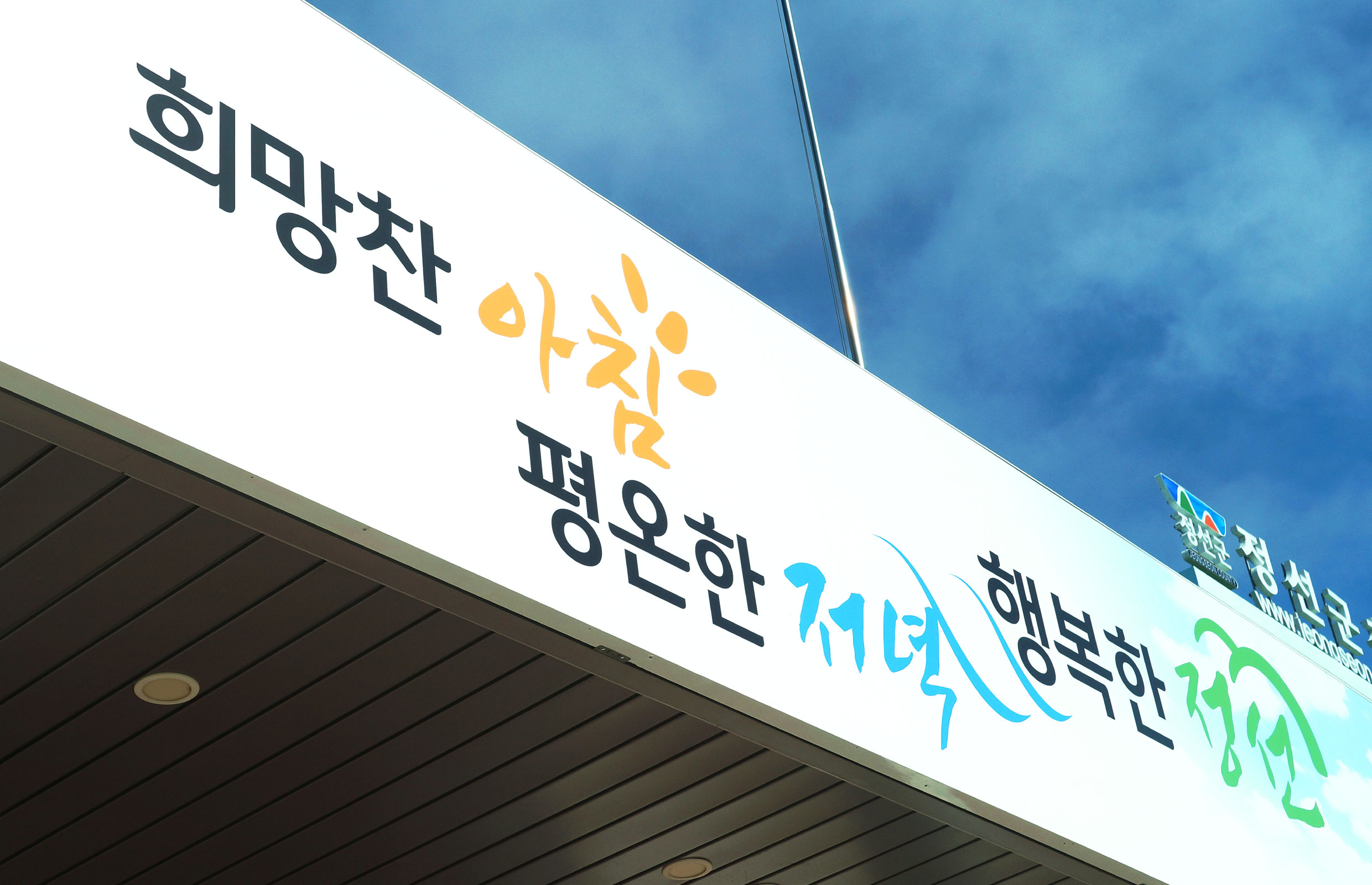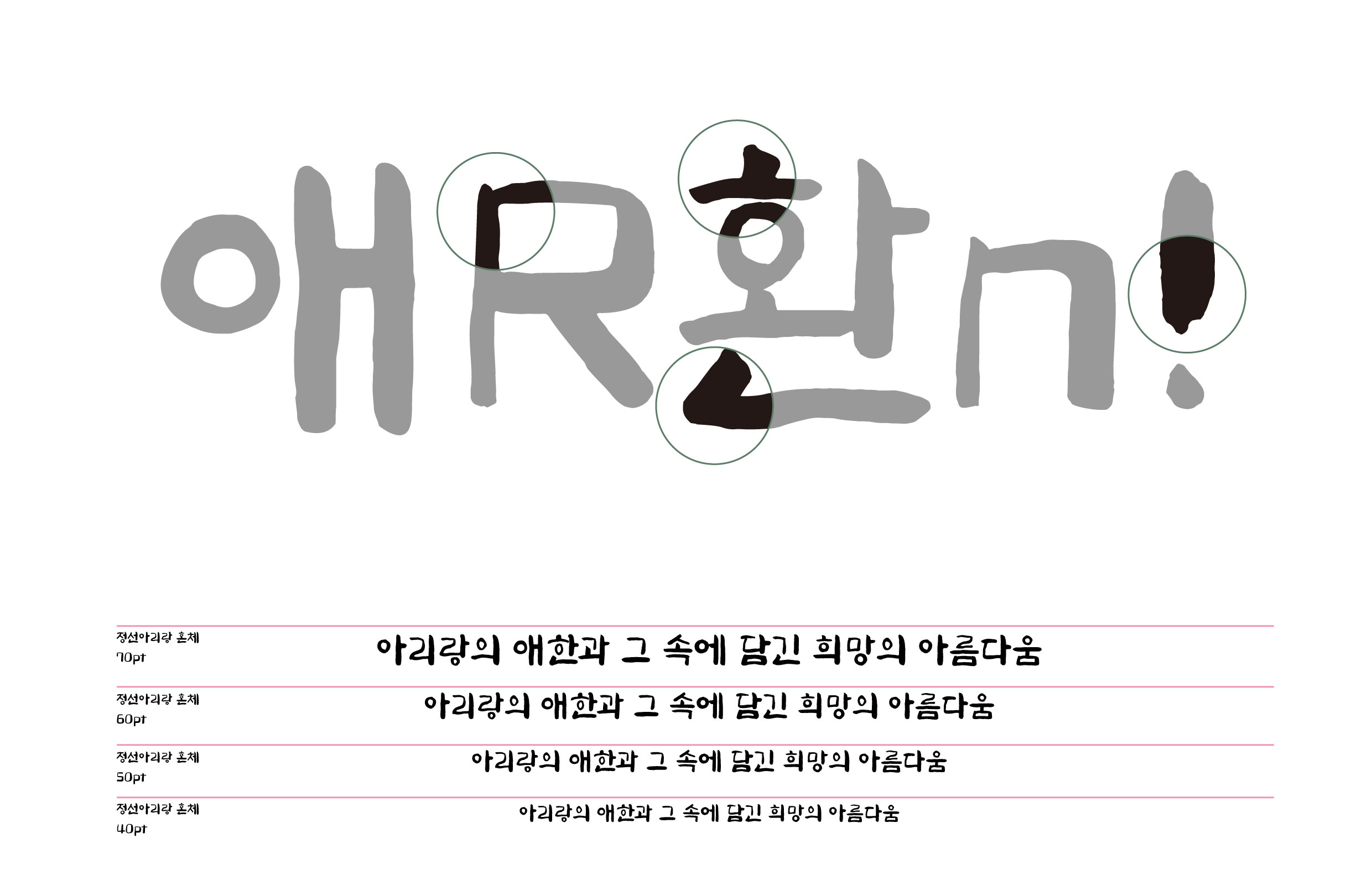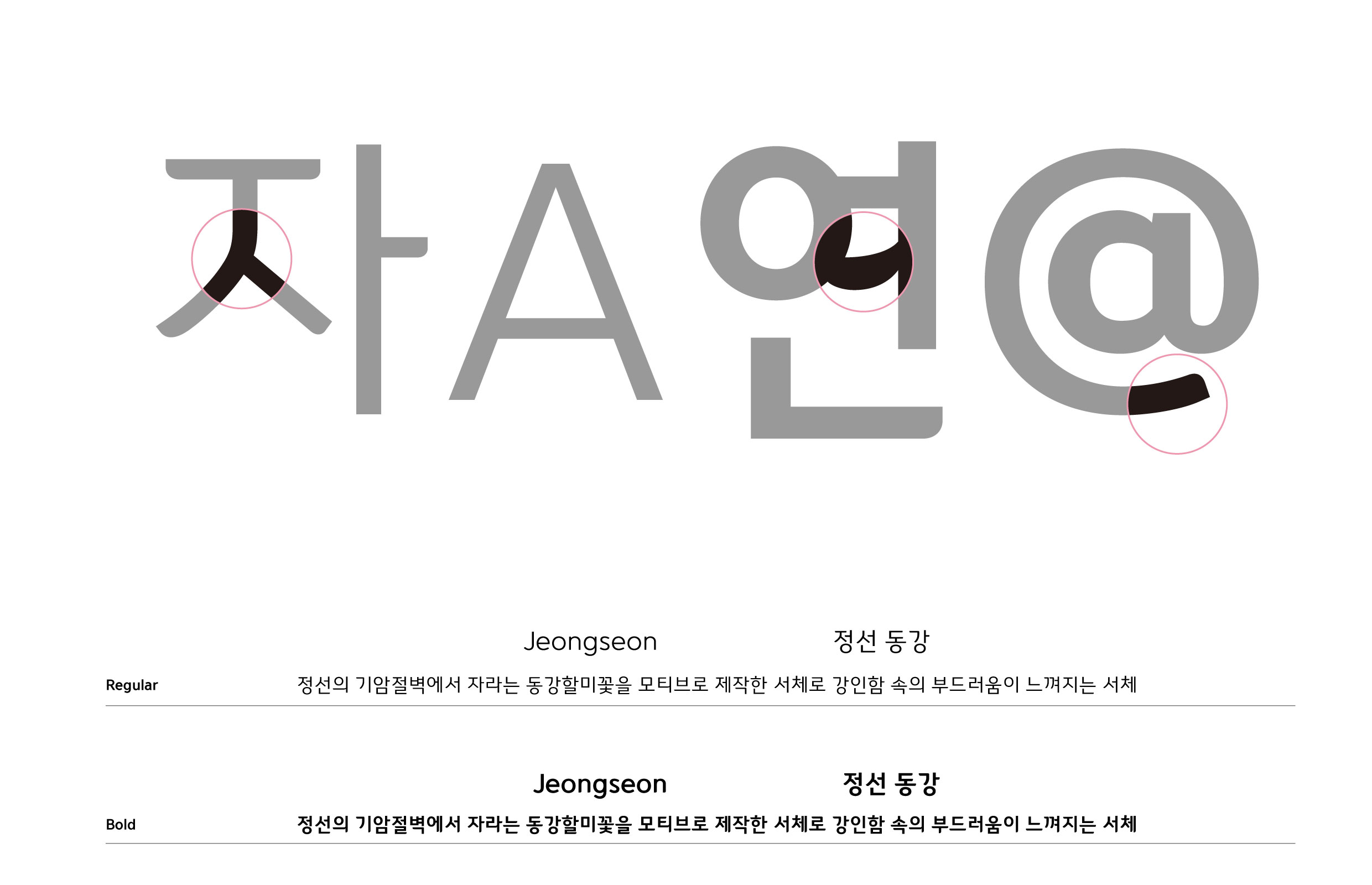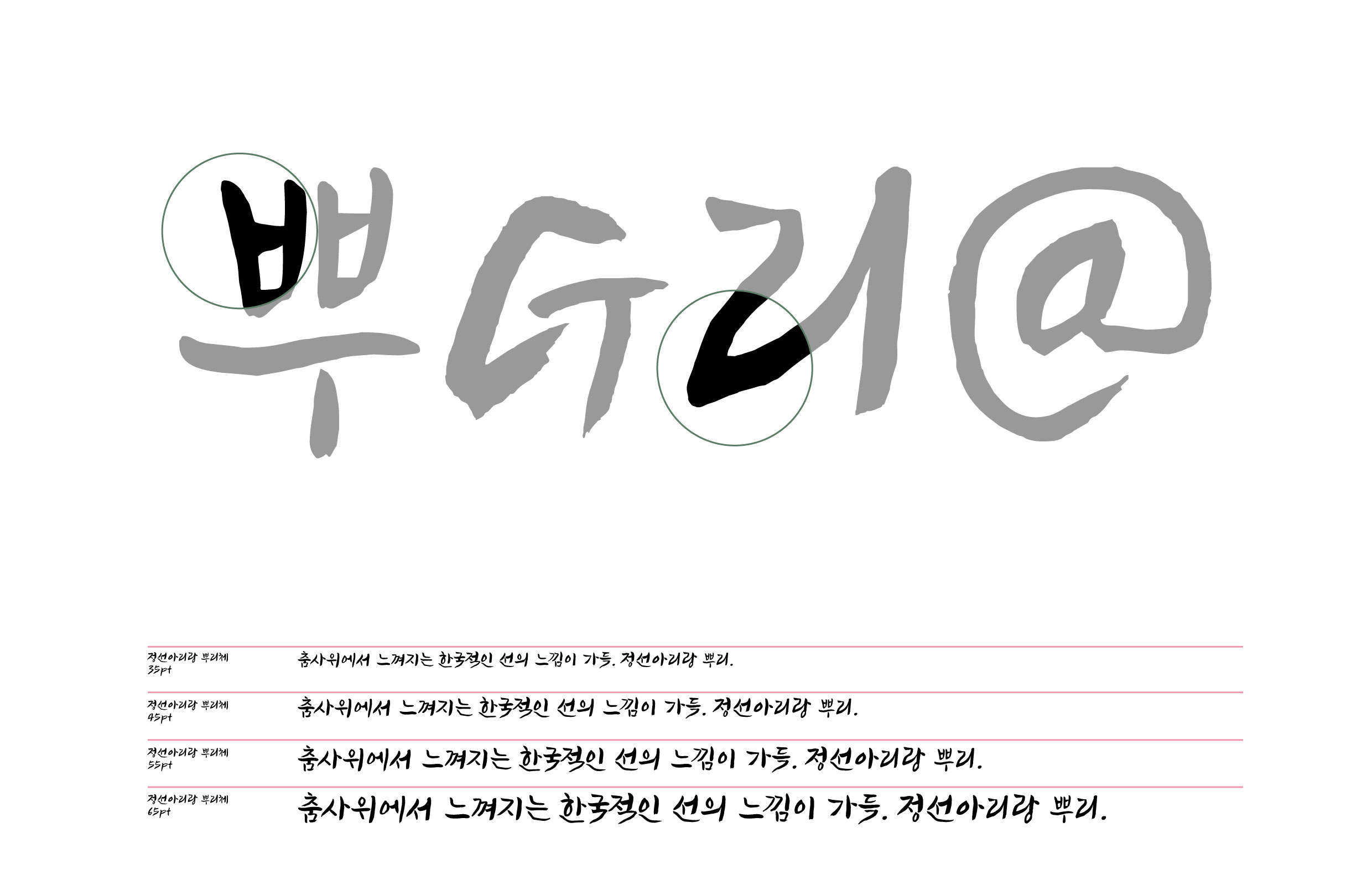
정선군
정선군 [정선아리랑체, 정선동강체]
정선군을 대표하는 정선아리랑과 동강을 표현한 전용서체. '정선아리랑체'는 힘이 있고 날카로운 느낌으로 아리랑 역사의 자존심을 이야기하며 정선아리랑의 비전과 희망을 표현했다. '정선동강체'는 정선의 기암절벽에서 자라는 동강할미꽃을 모티브로 디자인했다.